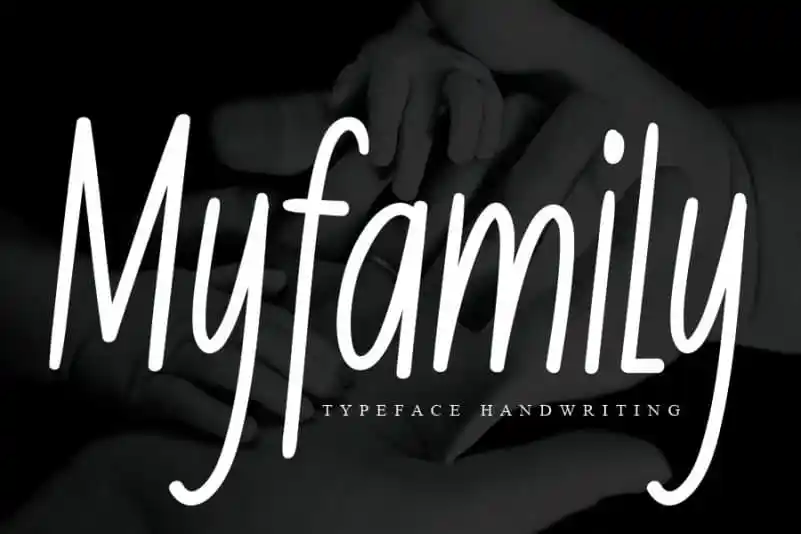
A Myfamily Handwritten Font é uma elegante escolha para aqueles que buscam uma fonte escrita à mão com características suaves e redondas. Seu estilo clássico, ao mesmo tempo amigável, torna-a perfeita para diversas aplicações gráficas. Suavemente inspiradora, ela é ideal tanto para as lindas cartas de cumprimentos quanto para as criativas postagens nas redes sociais e até mesmo como um toque sofisticado em convites de casamento ou arte de estação. Com essa fonte à mão, você não apenas adicionará um toque personalizado a seus projetos, mas também proporcionará uma sensação confortável e autêntica aos seus trabalhos. A Myfamily Handwritten Font é perfeita para quem busca uma fonte que seja tanto versátil quanto encantadora.